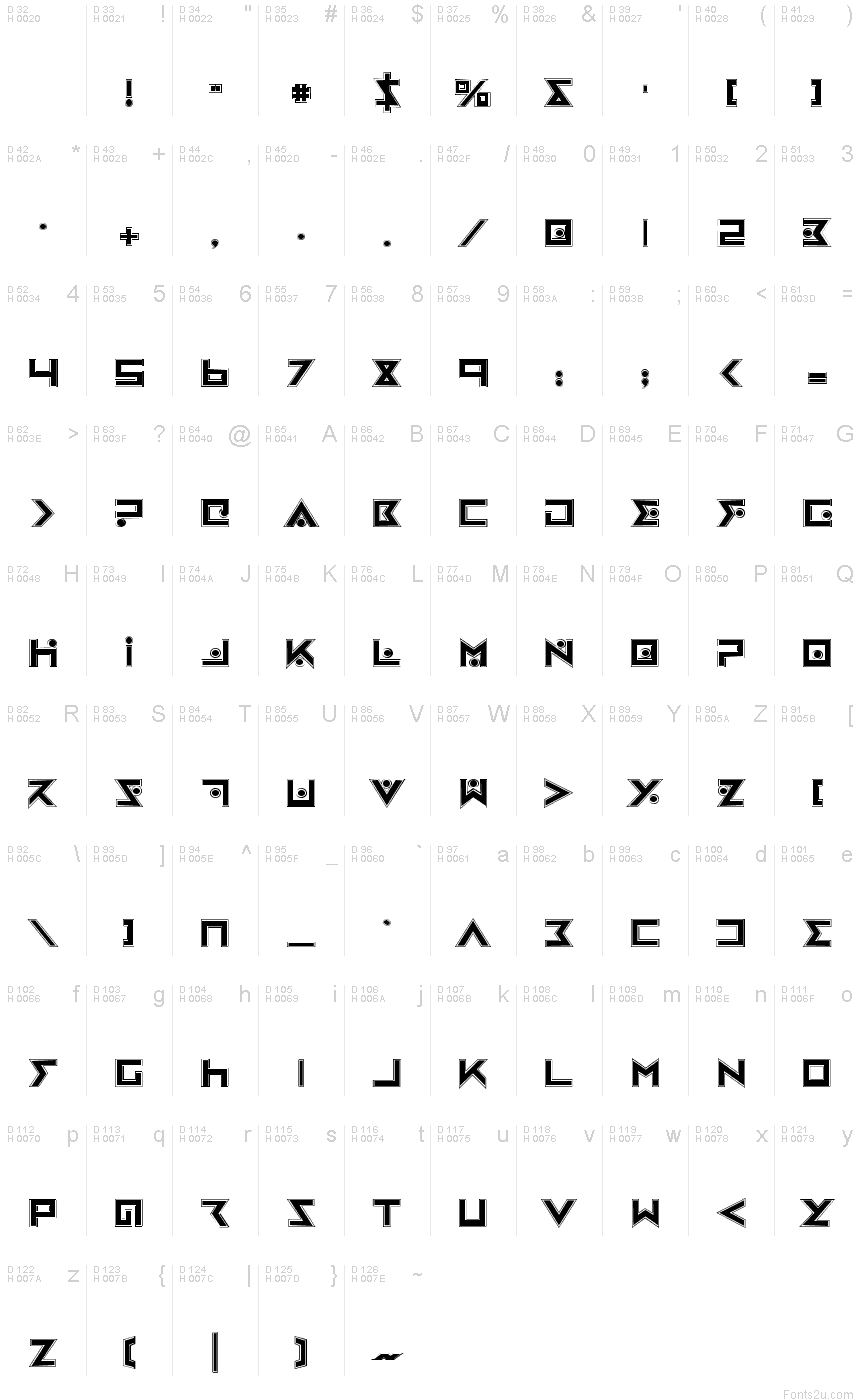
Iron Cobra Pro, darmowy techno font typu display od Iconian Fonts, buduje wyrazisty klimat sci-fi dzięki fazowanym narożnikom, ostrym przekątnym i wkomponowanym liniom, które sprawiają, że litery wyglądają jak opancerzone i zaprojektowane z inżynieryjną precyzją. Formy są szerokie i mocne, ale powtarzające się ostre kąty nadają im dynamiki, zamiast przytłaczać ciężkością, co dodaje krojowi napięcia rodem z ery automatów arcade.
Pasuje idealnie do logotypów gier, nagłówków plakatów, okładek albumów, plansz tytułowych czy brandingów w stylu naszywek, gdzie darmowy font ma nadać futurystycznego charakteru, nie stając się przy tym tylko ciekawostką. Używaj go wszędzie tam, gdzie krótkie słowa potrzebują tego pancernego, mechanicznego uderzenia, zwłaszcza w nazwach i tekstach na okładkach, które skorzystają na jego kanciastym rytmie.
Iron Cobra Pro